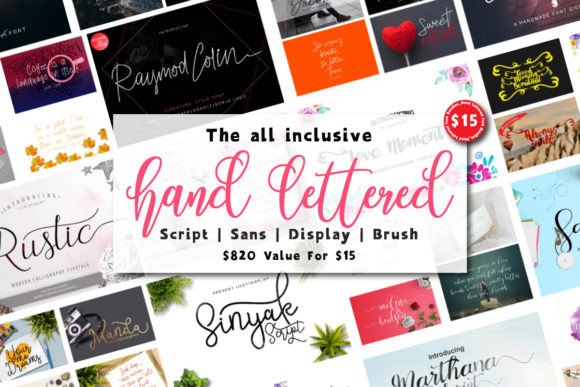
Hand Lettered Font Bundle
Trouver les bons éléments de conception peut être un défi, mais Hand Lettered Font Bundle propose une collection exceptionnelle qui rehausse instantanément votre travail.
Que vous créiez des produits POD (impression à la demande), des invitations de mariage ou des visuels pour les réseaux sociaux, Hand Lettered Font Bundle est un choix idéal.